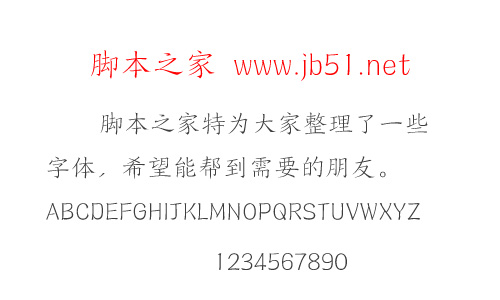
方正盛世楷書簡體字體(常規(guī)體)是方正盛世楷書簡體系列中最普通的一款常規(guī)體,該字體筆畫新穎獨特,字形飄逸大方得體,整體效果非常出色 ,且字庫完整,可以廣泛應(yīng)用于橫幅標(biāo)語、美術(shù)設(shè)計、宣傳海報、ppt、影視制作以及任何使用文字的領(lǐng)域,歡迎大家前來下載使用。